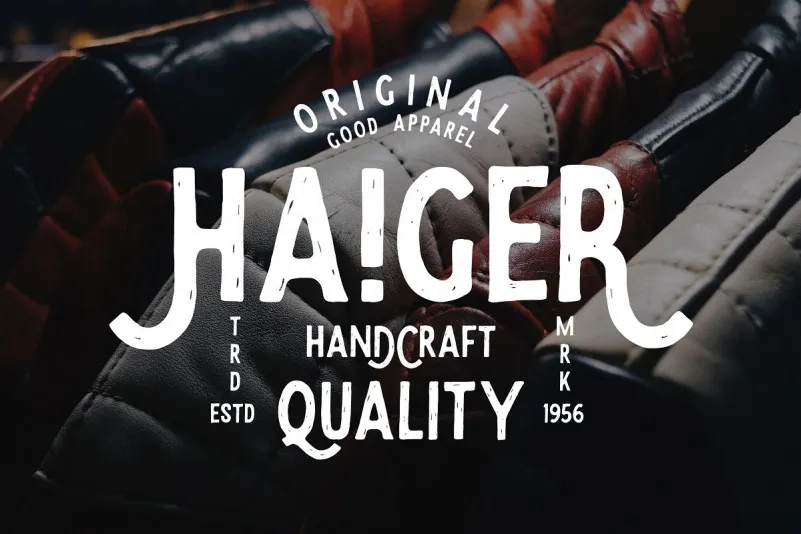
Eudora Vintage Label Font – Download Grátis
A Eudora Vintage Label Font é uma fonte display vintage que traz um toque único e fresco aos projetos digitais. Inspirada nas embalagens antigos e nas etiquetas de rótulos, essa fonte exibe um tom natural, o que a torna perfeita para qualquer aplicação visual que seja valorizada por seu charme retro. Seja para criar uma identidade visual robusta, personalizar logotipos ou até mesmo dar toques estilizados aos textos, a Eudora é uma opção versátil e encantadora. Uma das suas principais vantagens é o seu design de caracteres vintage que traz um único charme moderno. Esta fonte é perfeita para criar rótulos de produtos com um toque clássico e elegante, ou para incorporar em materiais impressos como capas de livros ou revistas, dando um ar retrô a qualquer projeto. Além disso, sua textura natural permite que você personalize o design de seu projeto conforme necessário. Seja na criação de uma identidade visual para sua marca, reforçando suas ferramentas de logotipo, etiquetas e embalagens ou até mesmo como uma maneira criativa de adicionar um toque fashion aos seus materiais impressos, a Eudora é uma fonte perfeita. Ela é ideal tanto para uso isolado quanto quando integrada em qualquer projeto de design gráfico.